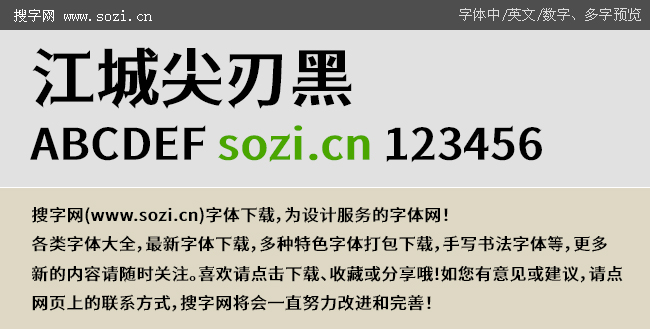
江城尖刃黑
搜字網(wǎng)給大家提供一款江城尖刃黑中文字體下載,江城尖刃黑是基于思源黑體改造的一款免費商用字體,這款字體是在獅尾福腿黑體SC的基礎(chǔ)上,把突刺三角放大,使其更加尖銳顯眼,把縱橫粗細(xì)比例差增加,使其縱橫分明,如利器般粗細(xì)不一縱橫交錯。適用于平面宣傳設(shè)計、網(wǎng)頁設(shè)計、海報設(shè)計等應(yīng)用。